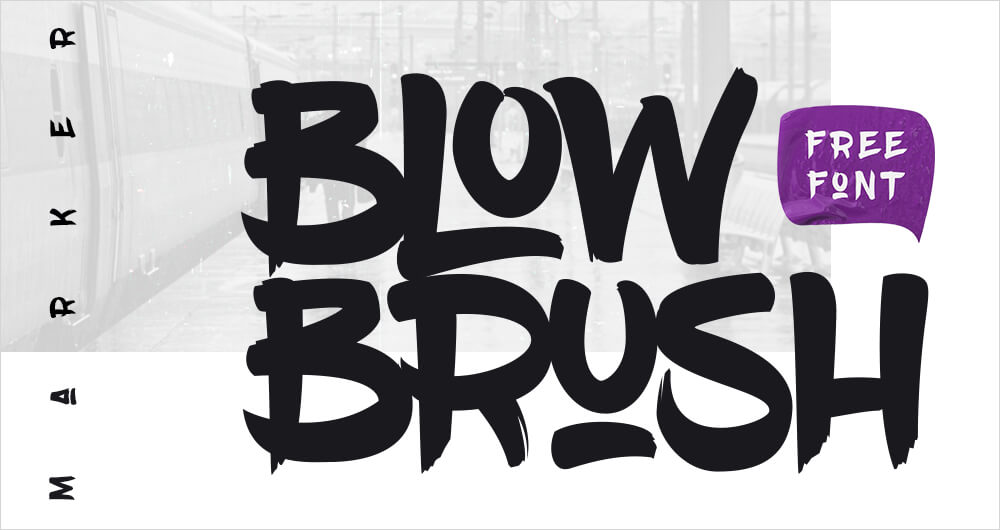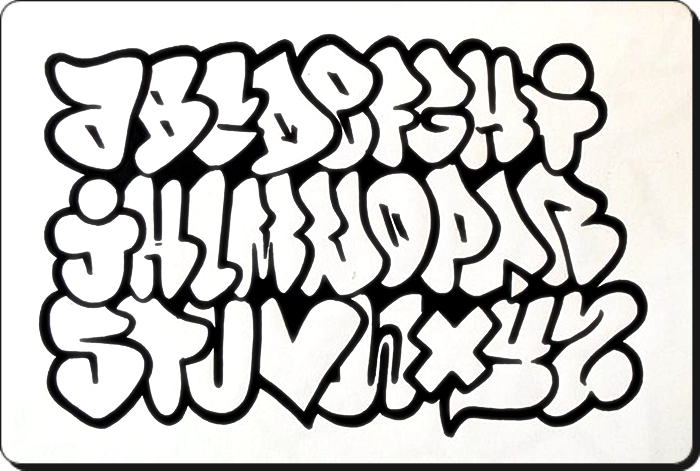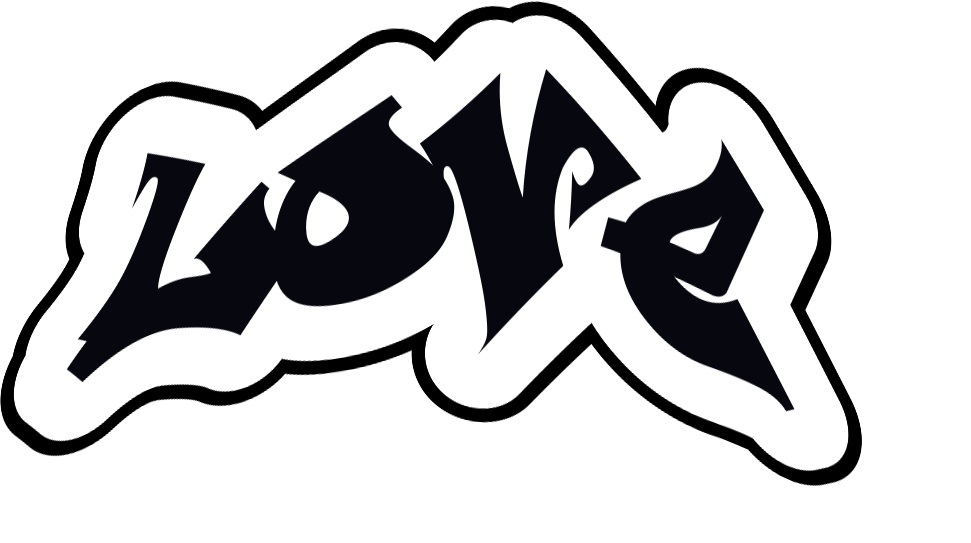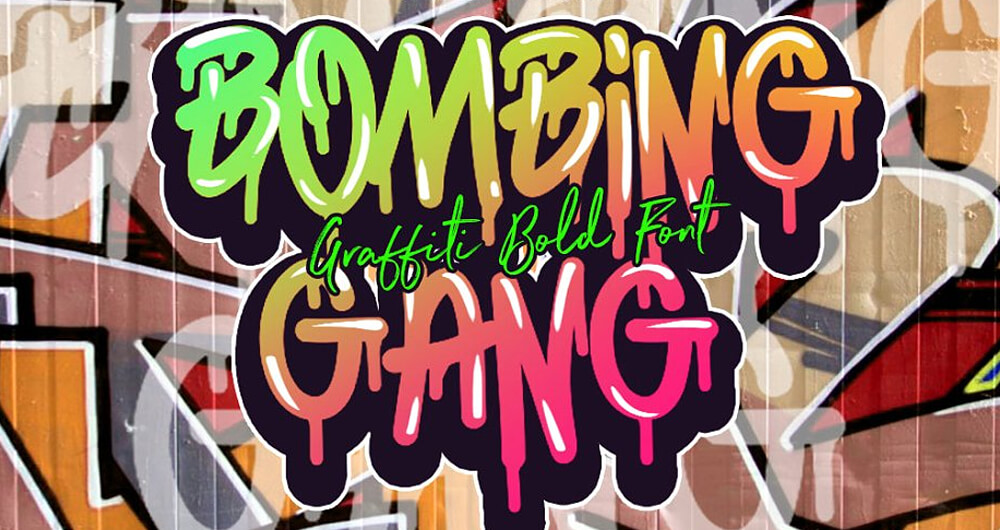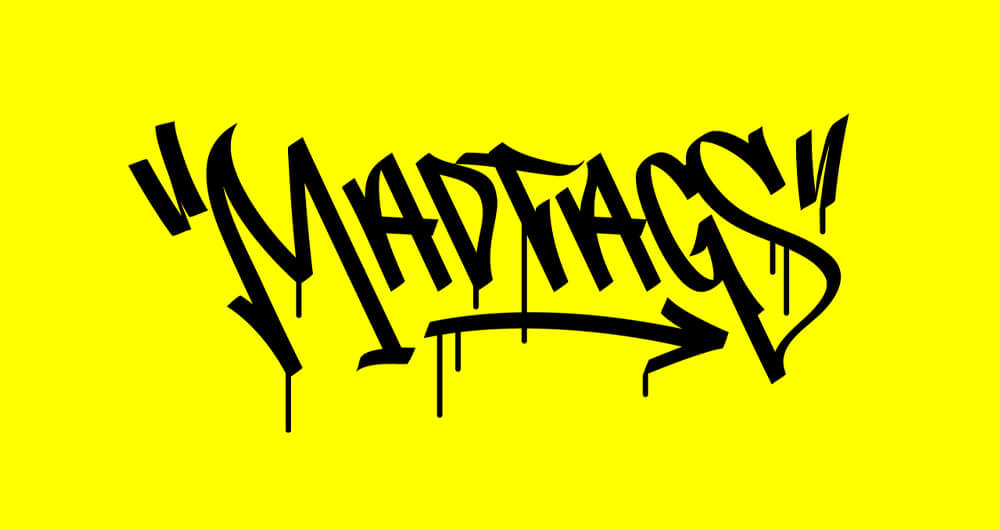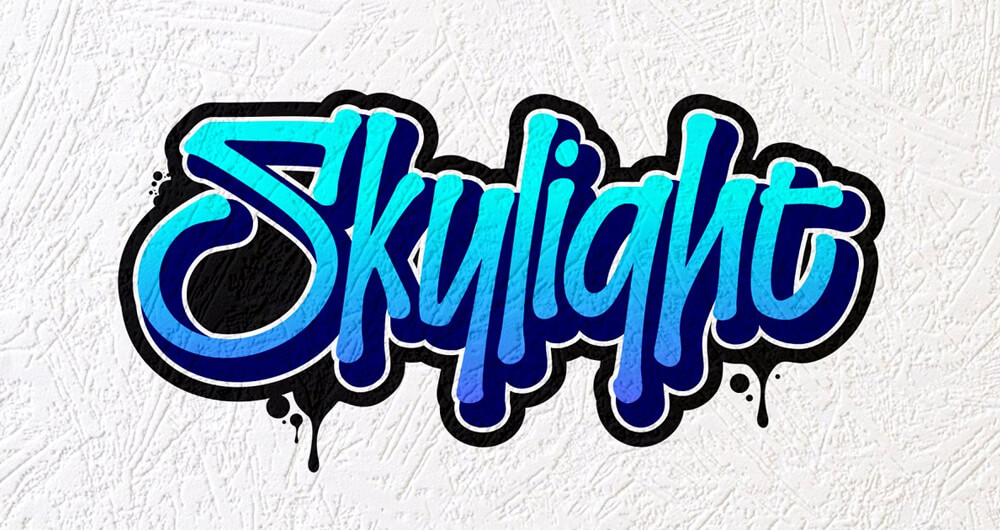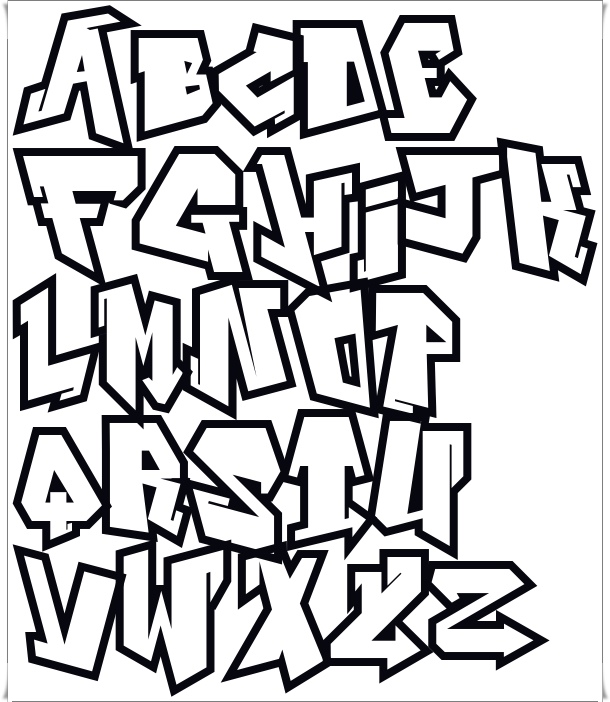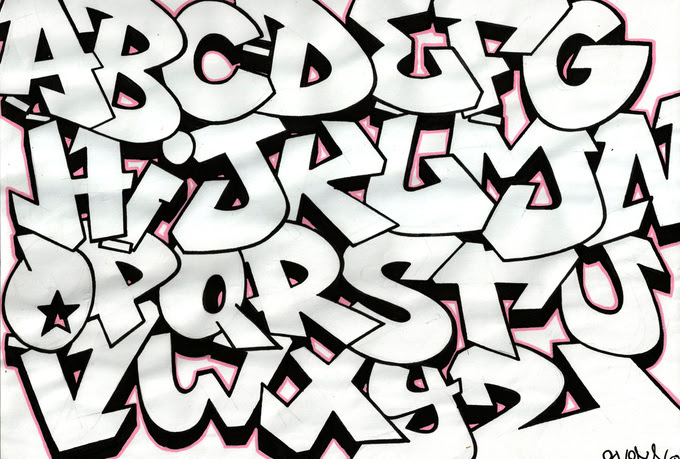
Graffiti Schriftarten Namen
Graffiti ist eines der schwierigsten Dinge, die Liebhaber verschiedener GraffitiStile und Schriftarten finden können Wir teilen weiterhin unseren Graffiti schrift, um so viel wie möglich zu helfen Sie können Ihren eigenen Stil erstellen, indem Sie die von uns veröffentlichten GraffitiMuster untersuchen und großartige Werke produzieren.
Graffiti Font Graffiti is an artistic expression that is usually done on public buildings, walls, or trains Use our graffiti generator to make your name look like it was spraypainted in the city. Name in Graffiti style Could do large scale on mural paper and display on walls in hallway Graffiti Namen Kunst Grundschule Graffiti Zeichnung Zeichenunterricht Jugendlich Kunst Bildende Kunst Graffiti Kunstideen Urbane Kunst. Ein Archiv kostenlos herunterladbarer Schriftarten Durchsuchen Sie nach alphabetischer Reihenfolge, Stil, Autor oder Popularität.
Obwohl auch hier das Anbringen von Namen (taggen) eine Rolle spielt, darf diese Art von Graffiti nicht mit dem Writing verwechselt werden 37 Als 1955 der Jazz Saxophonist Charlie „Bird“ Parker stirbt, erscheint kurze Zeit später der Spruch „Bird Lives!“ an den Jazzclubs in New York, für den sich später Ted Joans und einige seiner. GraffitiSchrift – kostenlos und kommerziell nutzbar Conventional Wisdom Bei diesem Font gibt es nur Versalien – mit Ausnahme des „ß“ Jedoch wurde eine minimale Anpassung bei den Buchstaben der Kleinschreibung gemacht So können Sie dennoch die Groß und Kleinschreibung, gemäß der Germanistik, anwenden. Hier bei FontRivercom runterladen!.